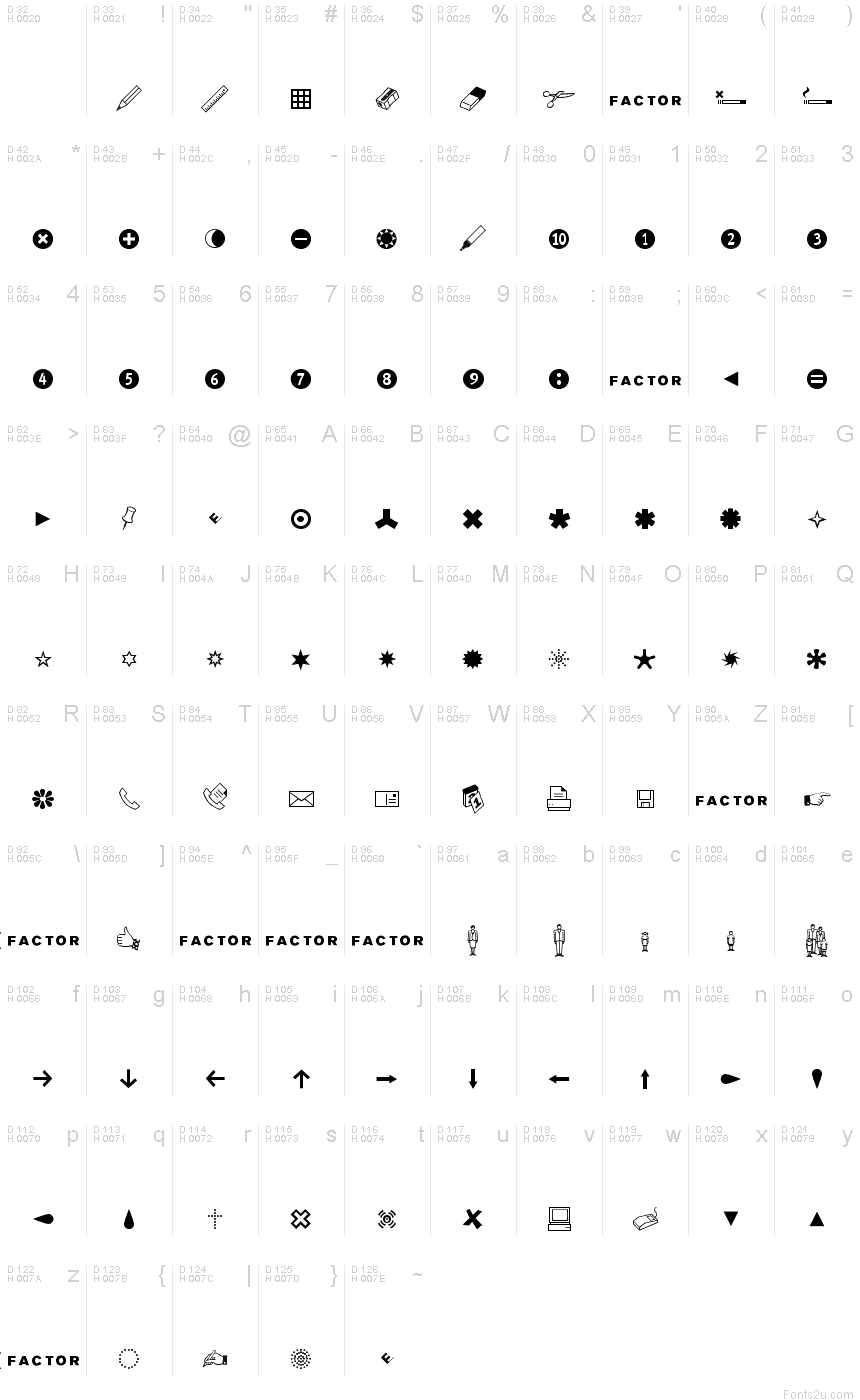
Dingbests von Johannes Erler ist ein kostenloser Piktogramm-Font aus dem Jahr 1997, der stumpfe Pfeile, massive Markierungen und eine reduzierte menschliche Figur zu einer sachlichen, fast schildartigen Formensprache verbindet. Die Icons wirken unaufgeregt und präzise statt verspielt; die schweren Silhouetten und die einfache Geometrie verleihen dem Set eine industriell anmutende Note, die an Leitsysteme erinnert.
Der Font eignet sich hervorragend für Plakatsysteme, redaktionelle Seitenleisten, Verpackungshinweise, Event-Grafiken und Labels im Interface-Stil, bei denen Symbole mehr bewirken als zusätzliche Worte. Als kostenloser Font bietet er sich zudem für Titelkarten, Trennseiten oder schnelle Branding-Akzente an – besonders dann, wenn Sie Symbole suchen, die robuster und weniger geschliffen wirken als herkömmliche UI-Icon-Sets.
Factor Design: Johannes Erler, published by FontShop International for the FontFont Library
Factor Design: Johannes Erler